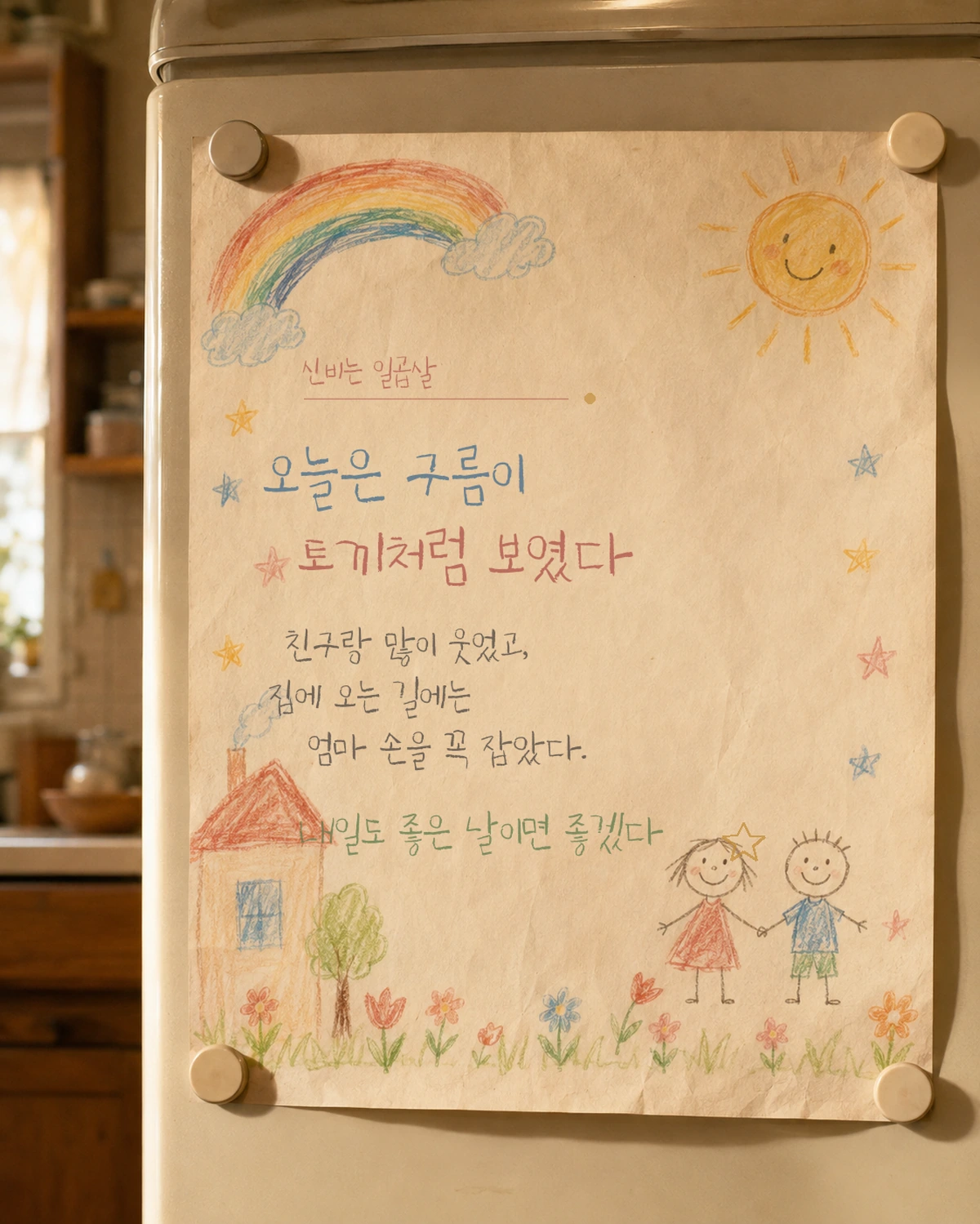
상상토끼 신비는 일곱살 — 상상토끼에서 배포하는 무료 폰트입니다. 일곱 살 아이가 색연필로 삐뚤빼뚤 써 내려간 듯한 순수하고 사랑스러운 손글씨체
상상토끼가 내놓은 손글씨 서체로, 원본을 쓴 사람이 일곱 살 아이입니다. 제작사가 남긴 설명에 사연이 그대로 담겨 있습니다. 삐뚤삐뚤 못생겼지만 일곱 살 꼬마의 순진무구한 감성이 폴폴 풍기는 사랑스러운 폰트이며, 아빠의 갑작스러운 부탁에 작은 손가락을 꾸물럭거리며 열심히 글씨를 써 준 신비에게 감사를 전한다는 것입니다.
형태는 파일에서 재어 봤습니다. 획이 가늘고 자면을 채우는 비율이 낮으며, 받침이 붙을 때 글자가 아래로 내려가는 탈네모틀이라 글줄이 공책에 쓴 것처럼 오르내립니다. 아이가 쓴 글씨의 리듬이 그대로 남아 있는 셈입니다.